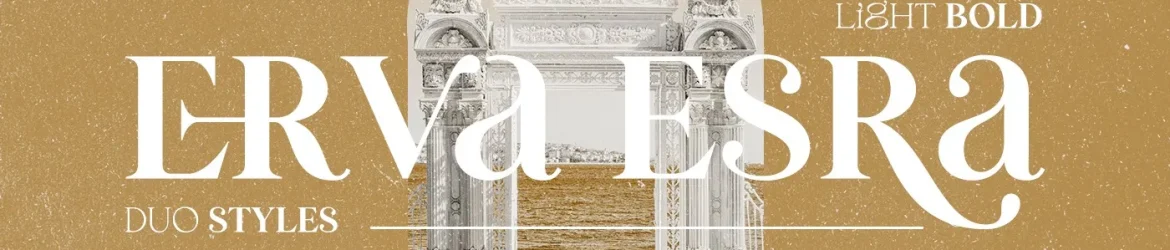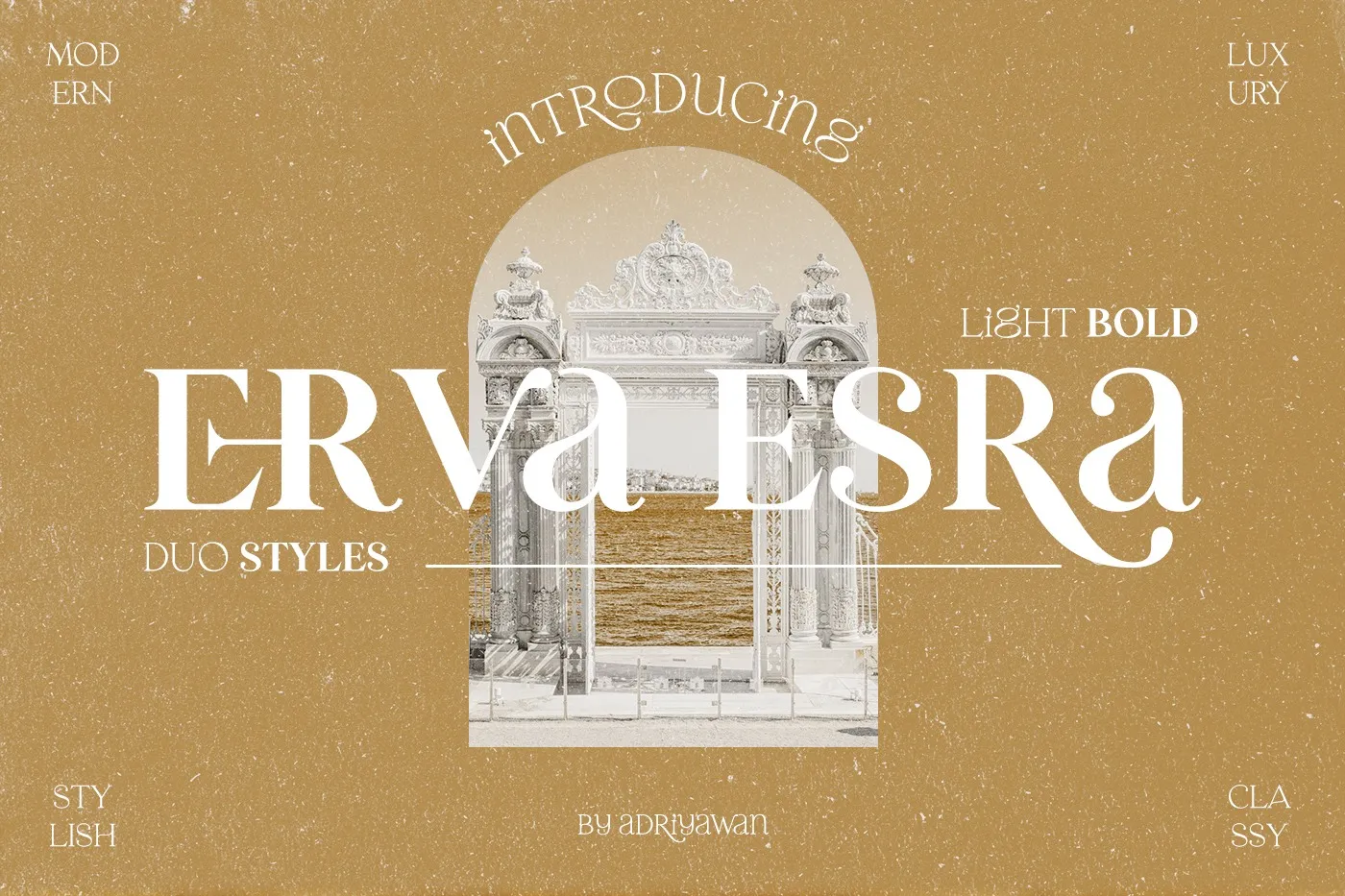
Erva Esra Font – Fonte Grátis
Erva Esra Font
A Erva Esra é uma fonte serif moderna e bold criada pela dxsign com um toque elegante. Esta família de fontes contém dois estilos: leve e bold, sendo perfeita para a criação de templates, brochuras, vídeos, branding publicitário, logotipos e muito mais. Seja você designer gráfico ou web, certamente encontrará esta fonte versátil e incrivelmente elegante que irá revolucionar seus trabalhos de design. Com um estilo atemporal e sofisticado, a Erva Esra oferece uma solução perfeita para manter seu trabalho impecavelmente bem-formatado e apresentacional no campo da design digital.